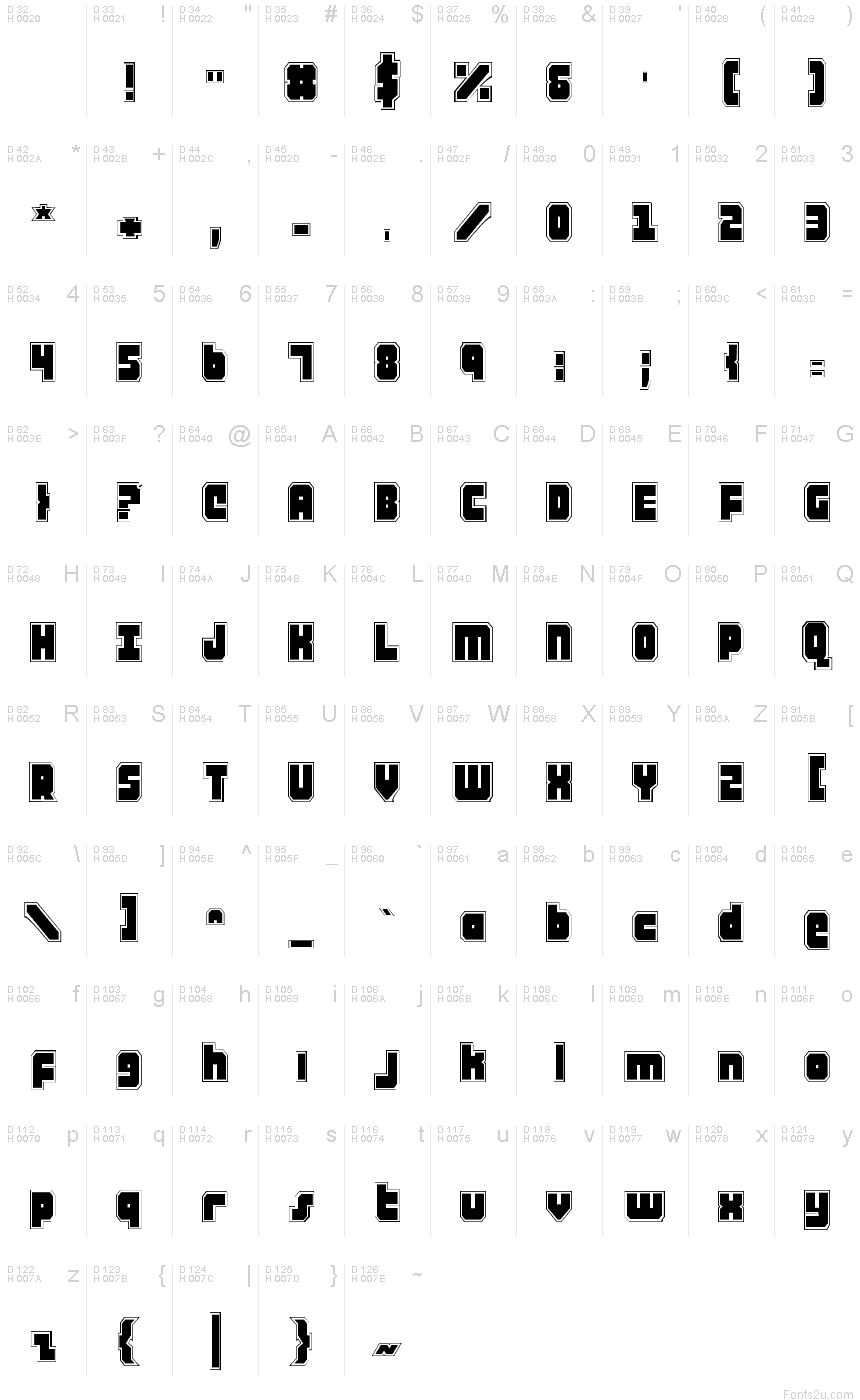
Alpha Taurus Pro od Iconian Fonts to darmowy, obrysowy krój typu techno display o wyrazistym, retro-futurystycznym charakterze. Litery zbudowano z masywnych, niemal ośmiokątnych form ze ściętymi rogami. Podwójna linia obrysu nadaje całości wygląd przypominający pancerz maszyny arcade, zachowując przy tym surowy, industrialny klimat.
Krój ten naturalnie pasuje do plakatów sci-fi, logotypów gier, plansz tytułowych, okładek albumów i klubowych ulotek, wszędzie tam, gdzie krótkie słowa potrzebują mechanicznego pulsu. Jako darmowy font, sprawdzi się również w eksperymentach brandingowych, grafice do streamingu i wyrazistych nagłówkach, zwłaszcza gdy wewnętrzny obrys wykonuje znaczną część wizualnej pracy.